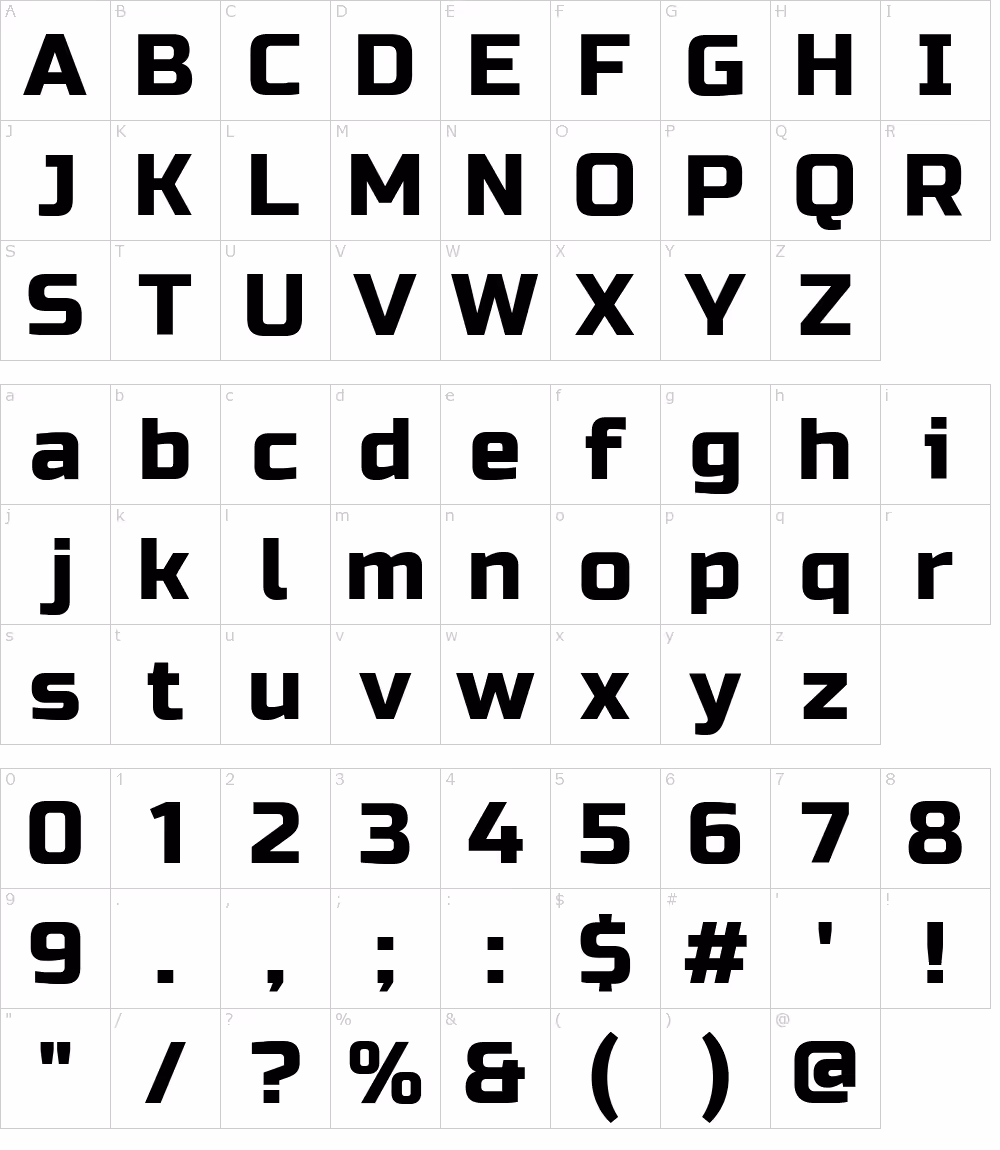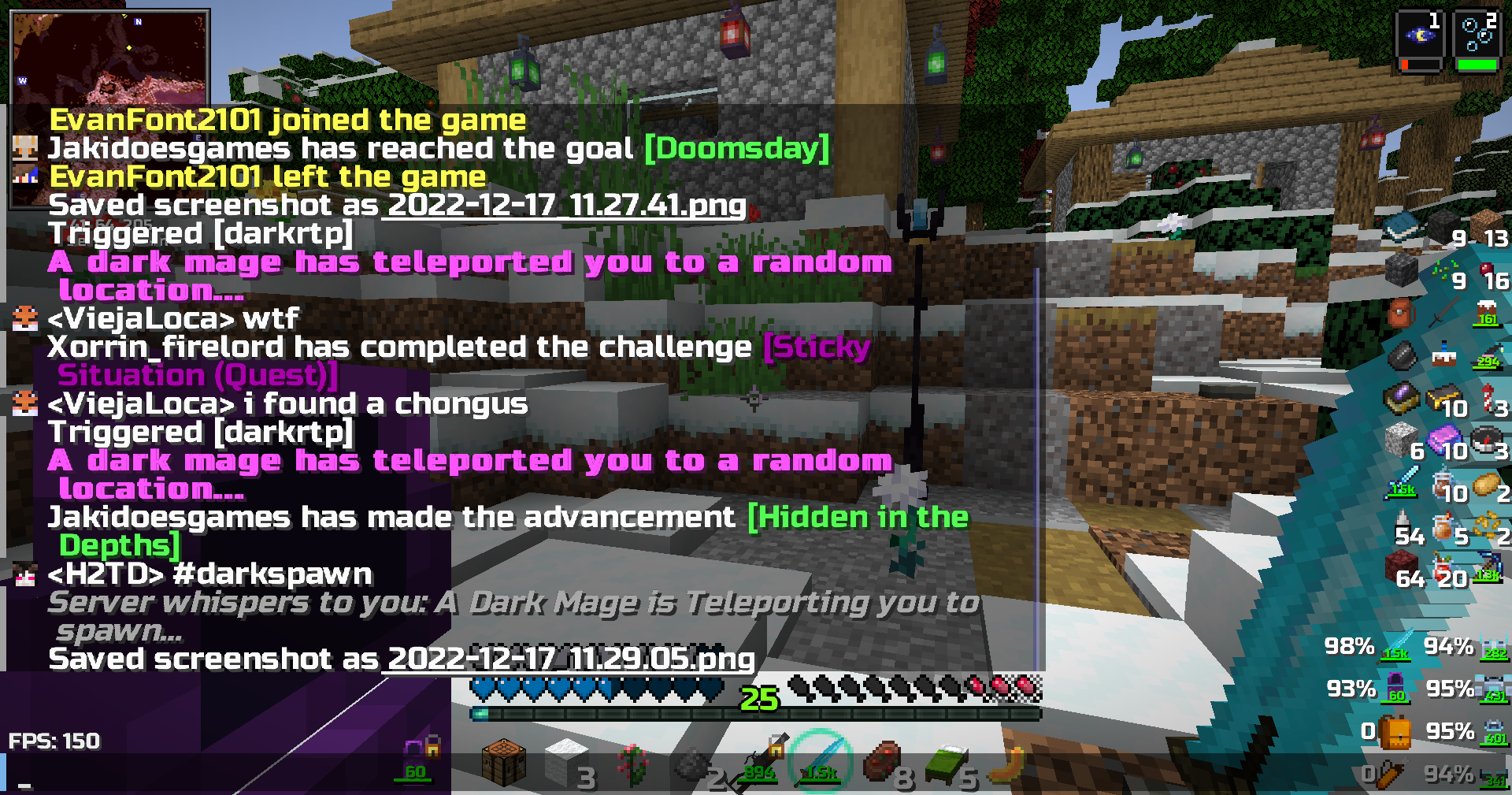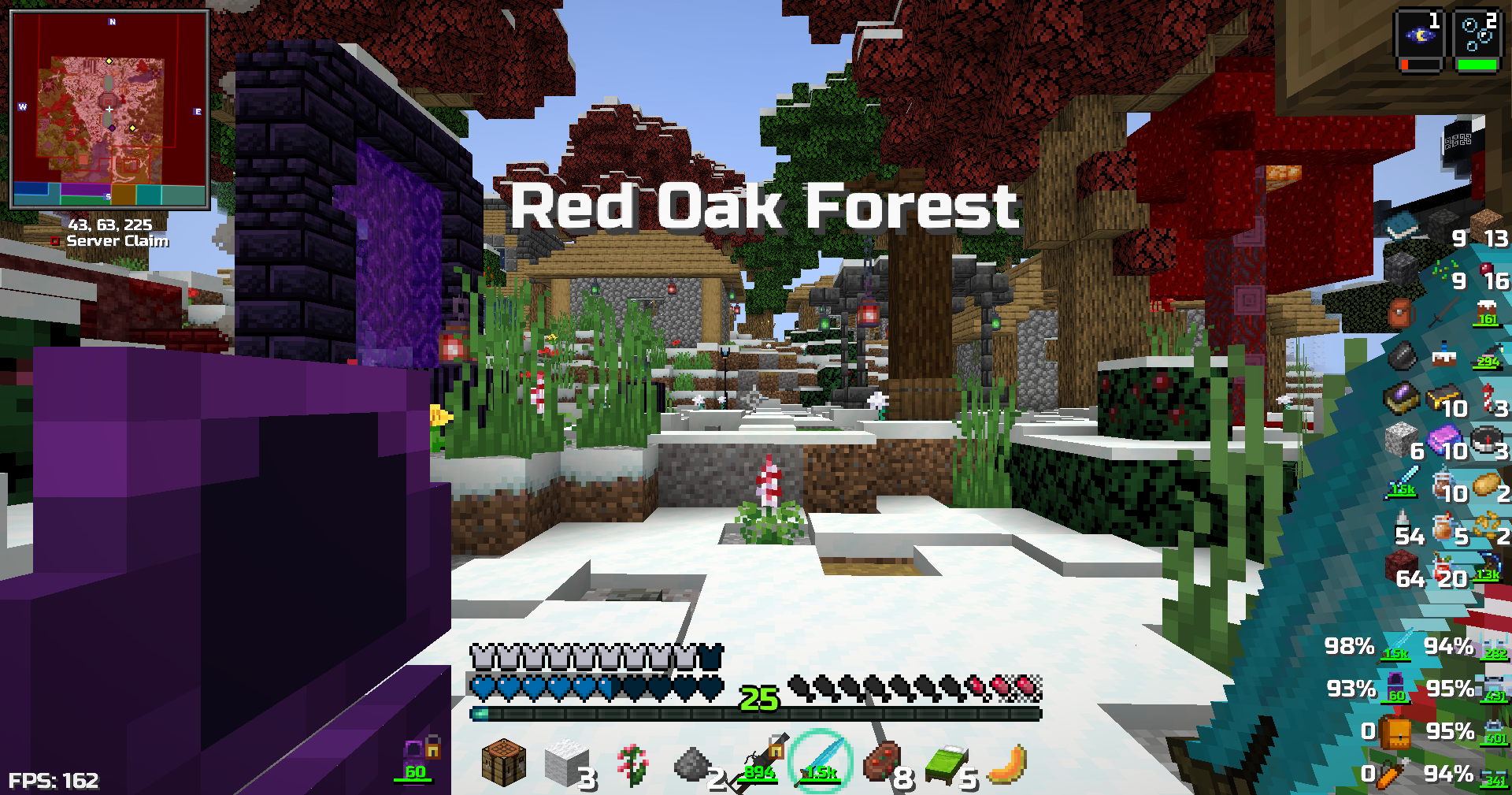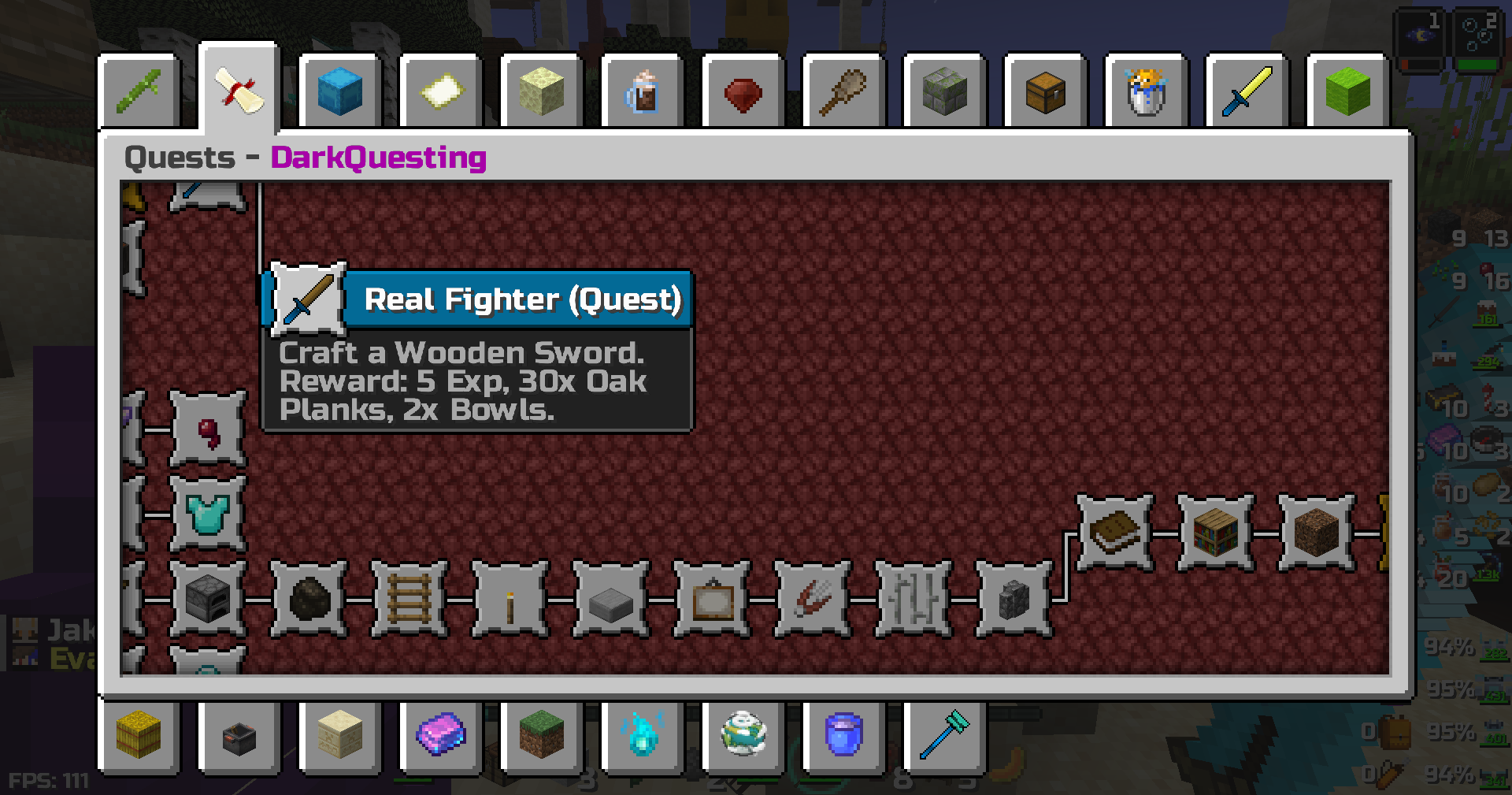
Avec Super RPG Font, la lisibilité du texte dans Minecraft prend une toute nouvelle dimension. Conçu à l’origine pour le modpack DarkRPG, cet add-on de police est désormais accessible à tous les joueurs souhaitant améliorer l’affichage des textes du jeu. Son style moderne et fluide apporte une clarté accrue, facilitant ainsi la lecture des dialogues, des menus et des interfaces.
Contrairement à la police de base de Minecraft, souvent jugée pixelisée et parfois difficile à lire sur certains écrans, Super RPG Font adopte une approche plus lisse et raffinée. Son design soigneusement pensé permet d’afficher des caractères plus nets et harmonieux, réduisant la fatigue visuelle, notamment lors de longues sessions de jeu.
Une Meilleure Visibilité du Texte
L’ajout de Super RPG Font améliore l’esthétique du jeu en rendant les textes plus agréables à parcourir. Que ce soit dans les livres enchantés, les panneaux, les dialogues des PNJ ou les menus du jeu, cette police apporte une meilleure lisibilité sans dénaturer l’univers de Minecraft. Elle conserve une cohérence visuelle avec l’ambiance cubique du jeu, tout en améliorant significativement la clarté des inscriptions.
Compatible avec Tous les Packs de Textures
Bien que développée pour DarkRPG, cette police fonctionne avec n’importe quel pack de textures, offrant ainsi une flexibilité totale aux joueurs souhaitant l’intégrer à leur univers personnalisé. Son installation simple permet de l’adopter rapidement et de bénéficier immédiatement de son effet amélioré sur l’affichage des textes.